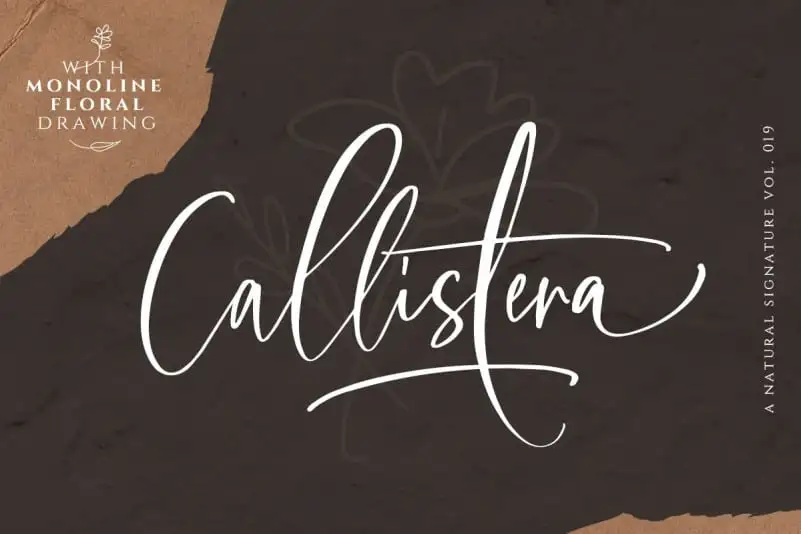
Callistera Script Font – Download Grátis
A Callistera Font é uma elegante tipografia script moderna, projetada com uma escrita cuidadosamente elaborada, que transmite sofisticação e elegância através de sua linguagem fluida e expressiva. Com letras minúsculas, maiúsculas e símbolos, ela se destina a qualquer aplicação, como gráficos de logotipo ou design de moda requintado. Ideal para invitações de casamento ou citações escritas à mão, essa fonte tem ligaturas, alternativas contextualizadas e estilísticas, assim como suporte multilingue. Além disso, a Callistera Signature Script inclui letras em rotação livre (swash) e sublinhado, tornando-a ainda mais versátil para diversos ambientes de design, desde os mais sofisticados até aqueles que valorizam uma autenticidade única.